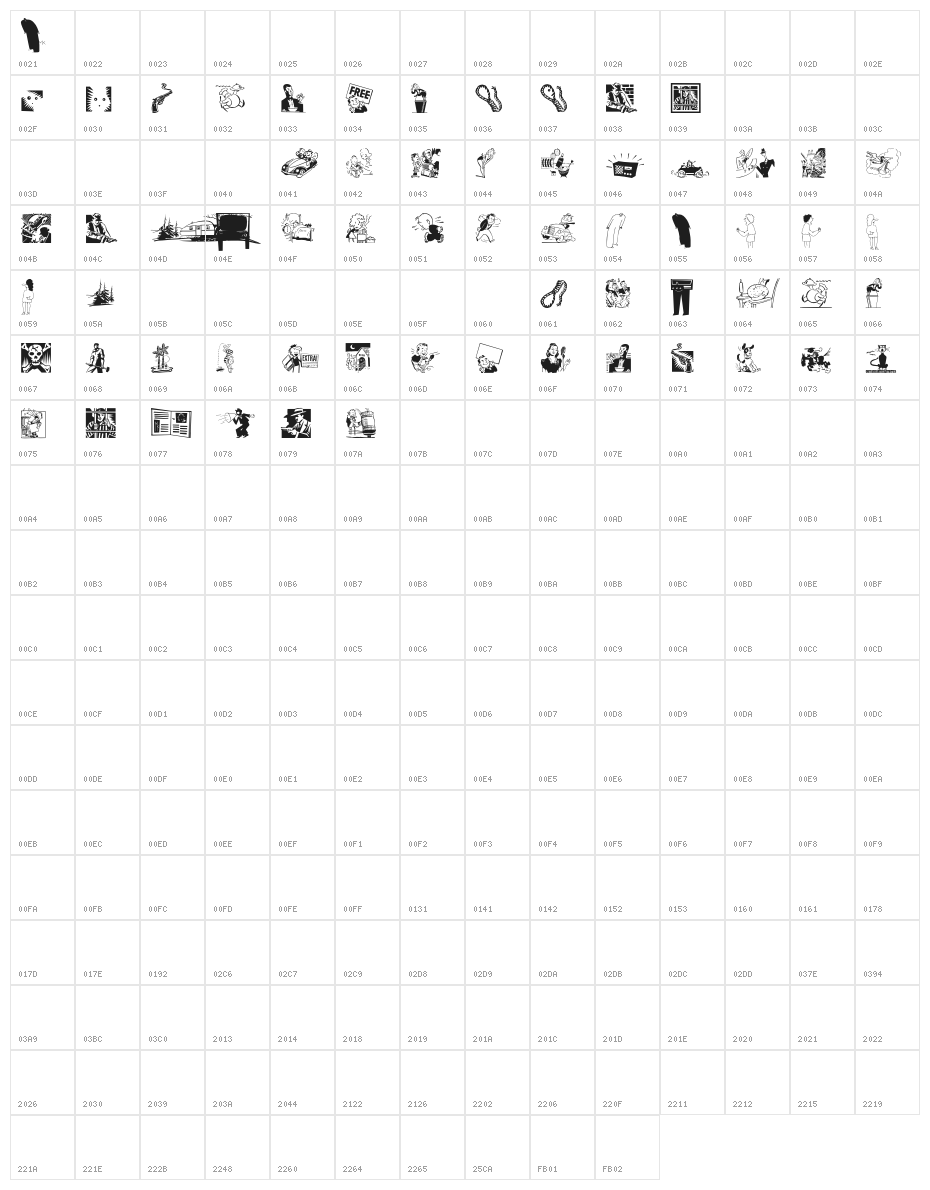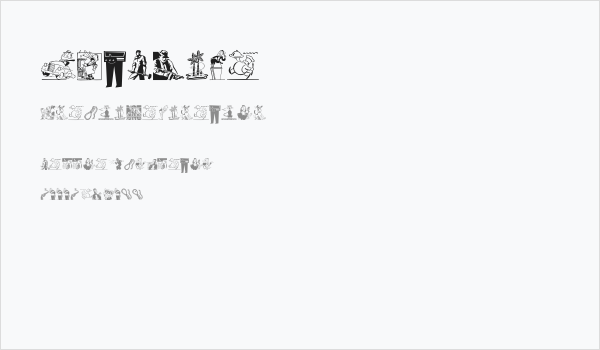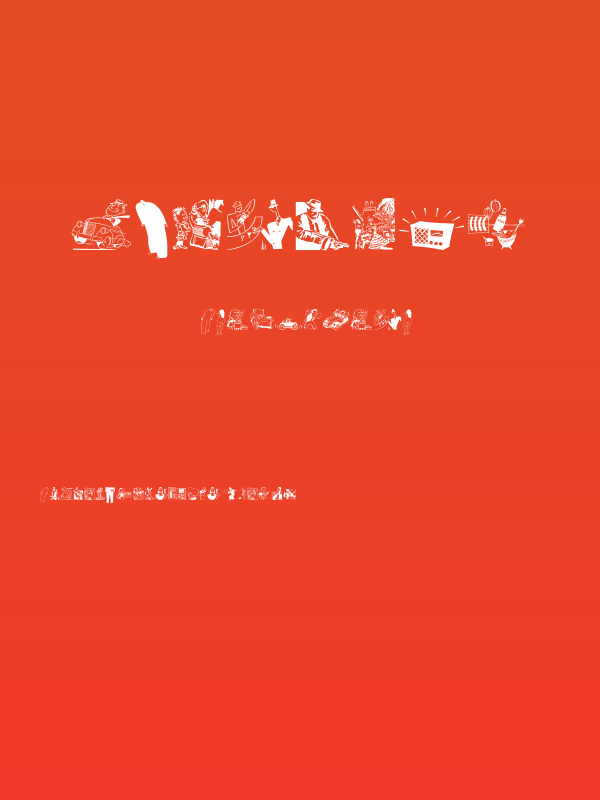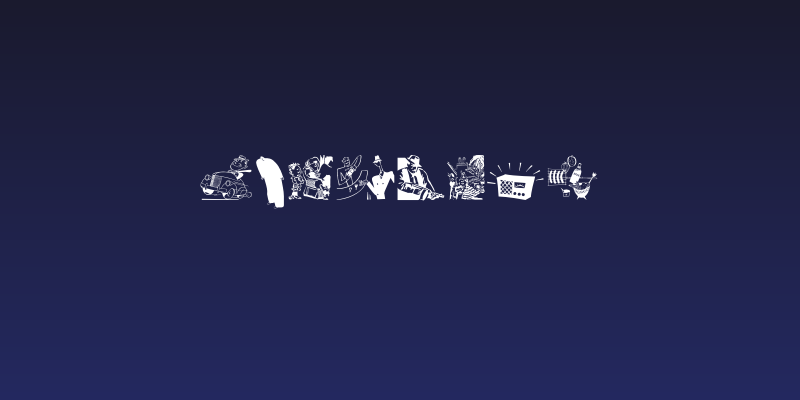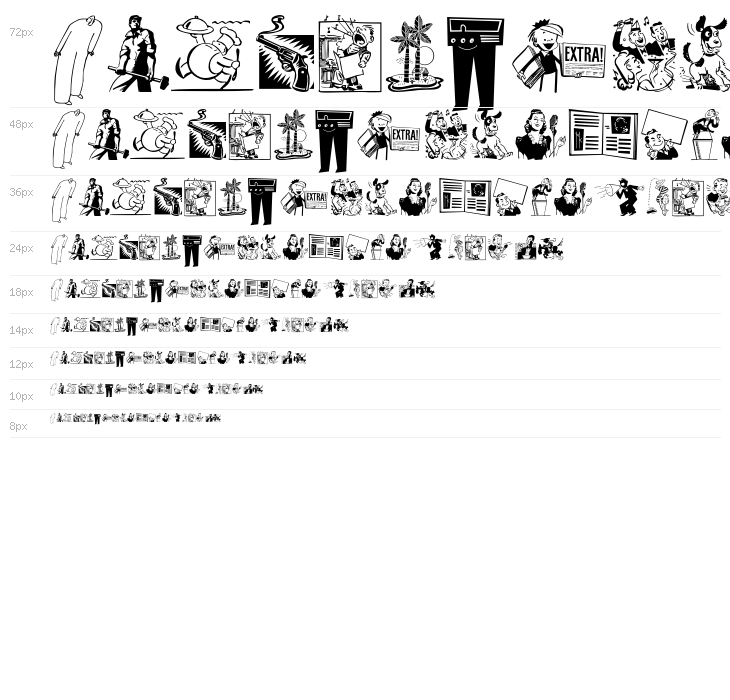
SuchLife Font
| Stile generale | Decorative, Retro, Cartoonish |
| Caso d'uso | Illustrative accents, posters, flyers, comics, novelty projects |
| Progetti proposti | Comic strips, editorial illustrations, retro posters, playful invitations, themed scrapbooks. |